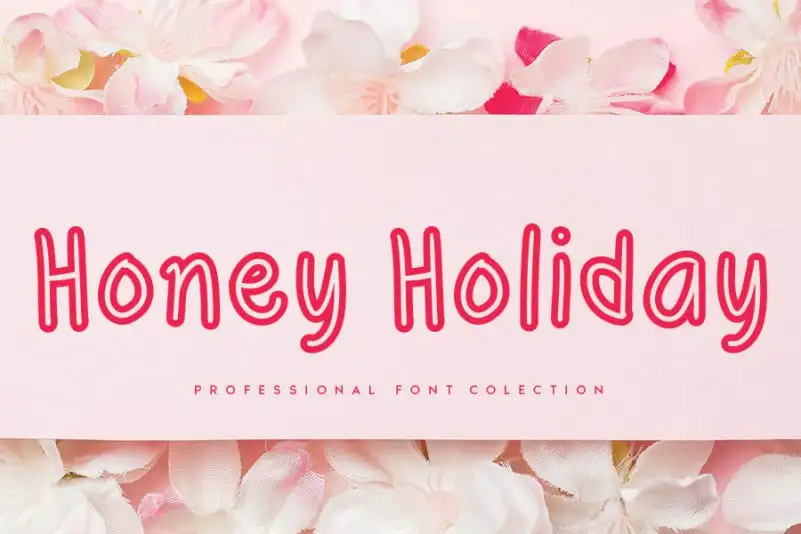
Honey Holiday Display Font – Fonte Grátis
Honey Holiday Display Font
A Honey Holiday Display Font é uma fonte handwritten que traz alegria para seus projetos digitais. Seu designer, Andikastudio, criou esta fonte com um toque convidativo e divertido que vai deixar seu trabalho mais charmoso e personalizado. Perfeita para aplicar em anúncios, logotipos, embalagens, cartazes, material de convites, ou até mesmo em elementos de água-marinha para imagens fotográficas. Além disso, ela é ideal para designs de produtos e assinaturas, tornando-se uma opção indispensável para qualquer projeto que valoriza um toque autêntico da mão humana. Em suma, a Honey Holiday Display Font é uma escolha ótima para quem busca um toque divertido e único em suas criações digitais.